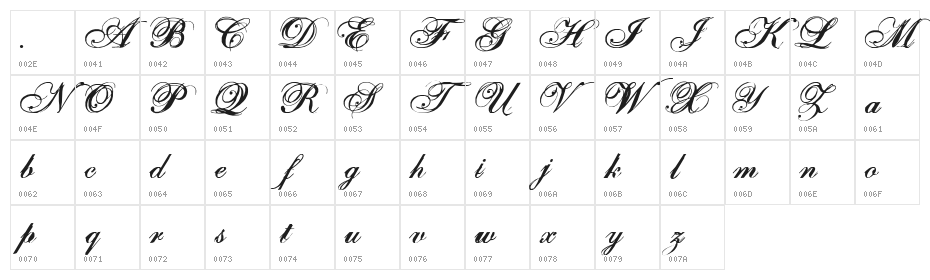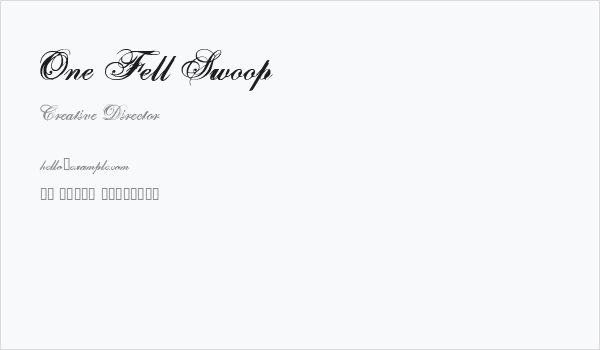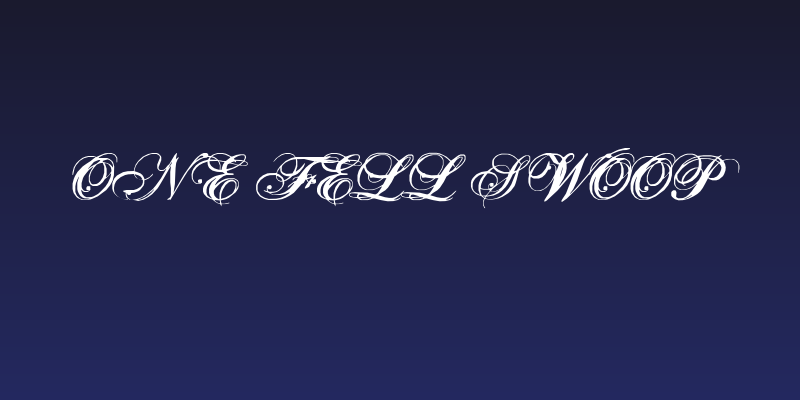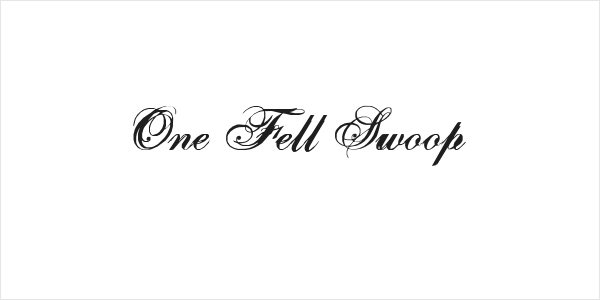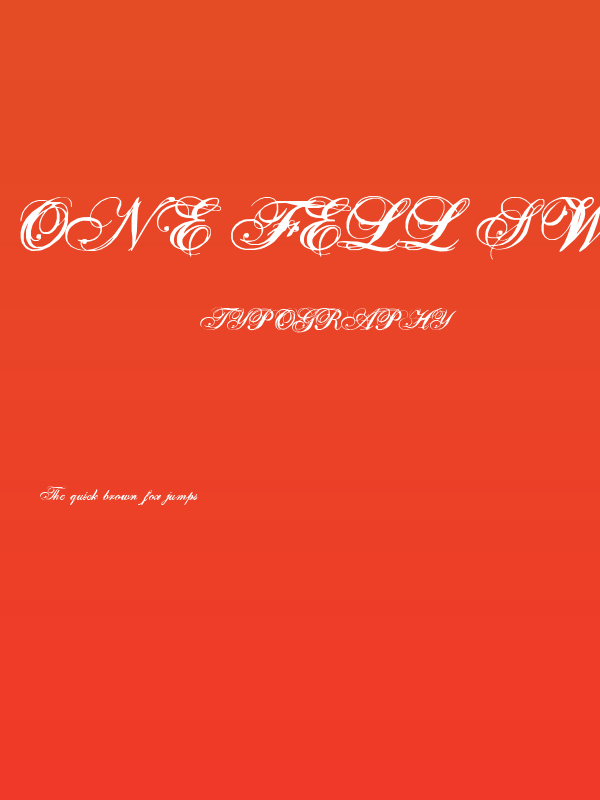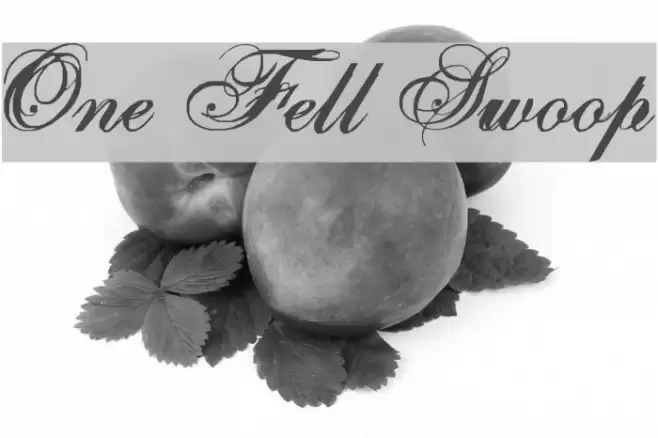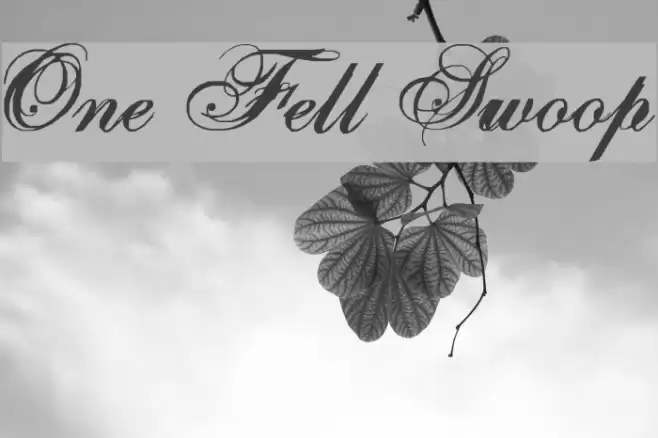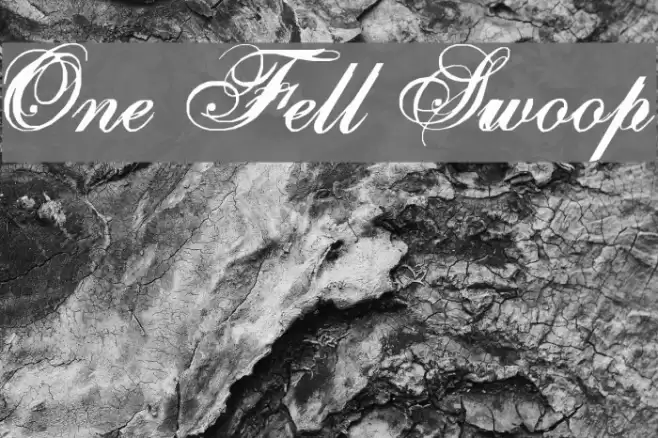
One Fell Swoop Font
✎ Calligraphic
| Caz de utilizare | Logos, Headlines, Invitations |
| Proiecte propuse | Ideal for wedding invitations, elegant branding, luxury product packaging, and decorative headlines. |